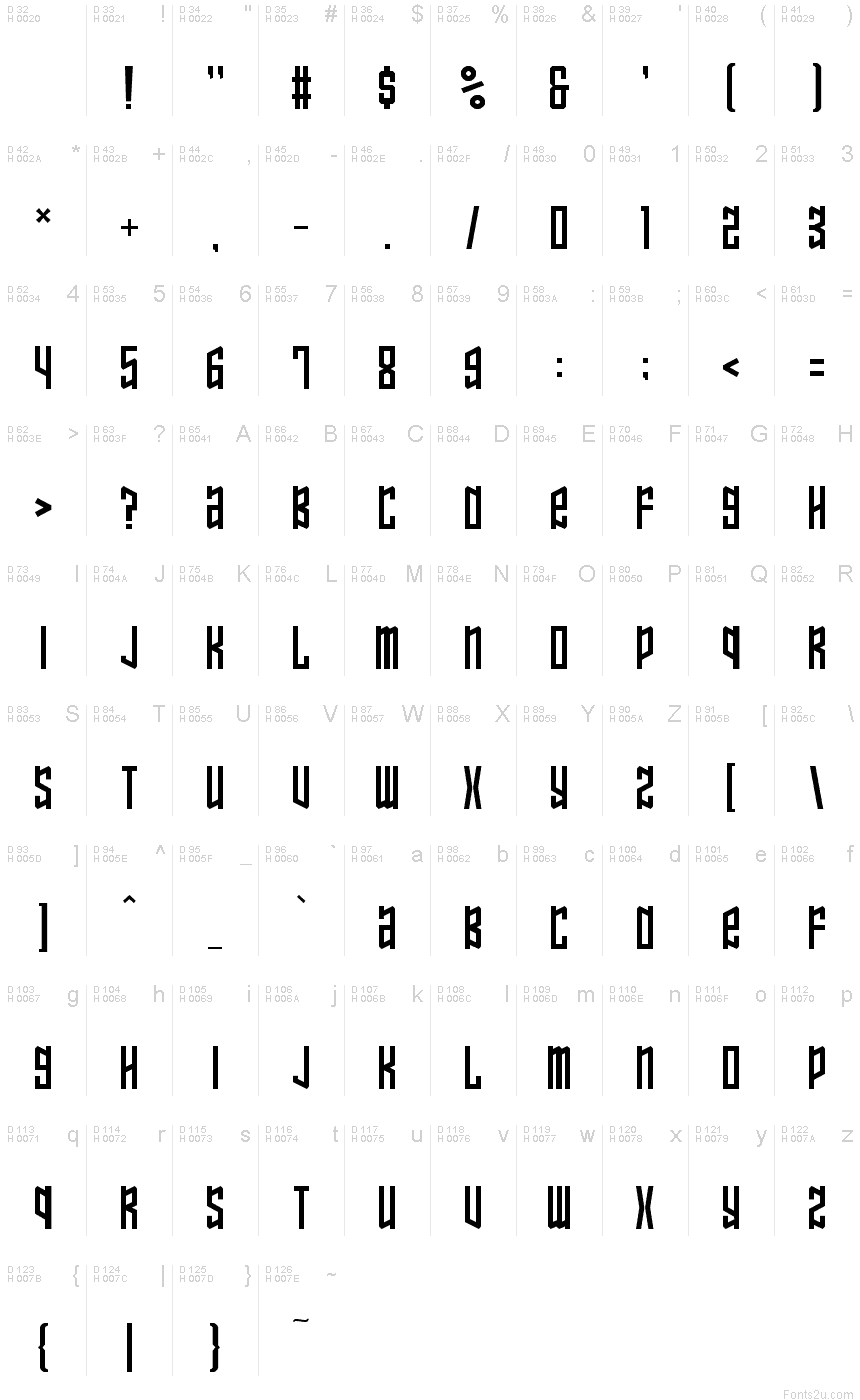
Ozone Layer
Ozone Layer di Jakob Fischer è un font display techno gratuito, caratterizzato da una silhouette alta e massiccia con angoli squadrati netti. Le lettere appaiono come forme di metallo tagliate, con aperture strette e intagli interni affilati che donano al carattere un ritmo meccanico, netto e una sensazione di compattezza.
Ozone Layer è perfetto per titoli sci-fi, grafica arcade, tech branding, poster, copertine di album e volantini per eventi che richiedono un deciso tocco digitale. Le forme angolari e l'allungamento verticale trasmettono un tono tecnico e ingegneristico privo di fronzoli; è quindi adatto anche per menu di giochi, motion graphic e loghi brevi.